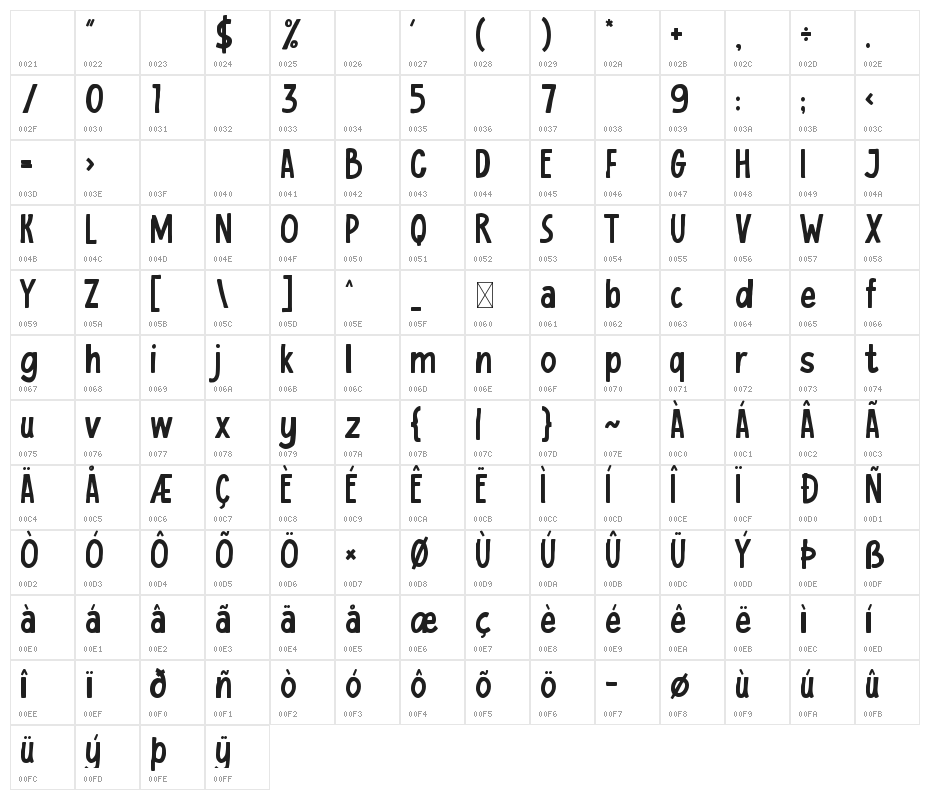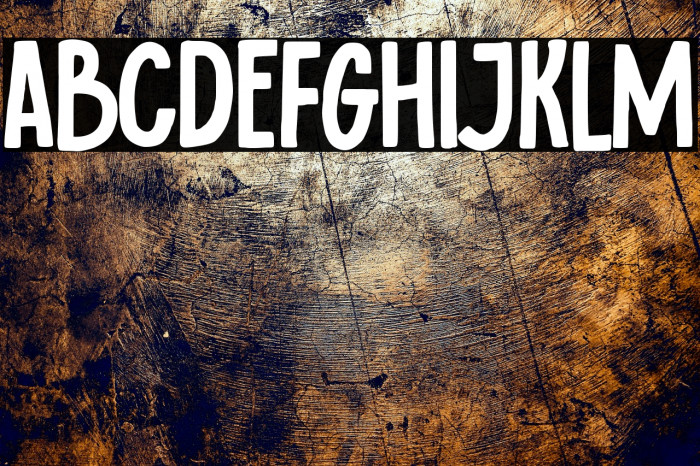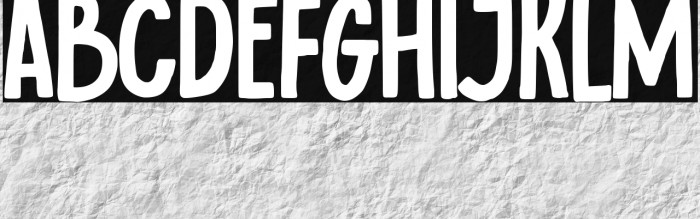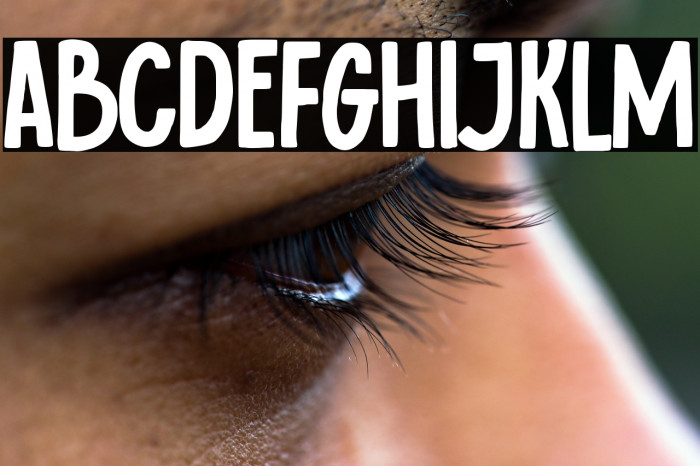
Bad Reason Font
| Gesamtstil | Playful, Whimsical, Informal |
| Vorgeschlagene Projekte | Ideal for children's books, playful branding, casual invitations, and creative posters. |